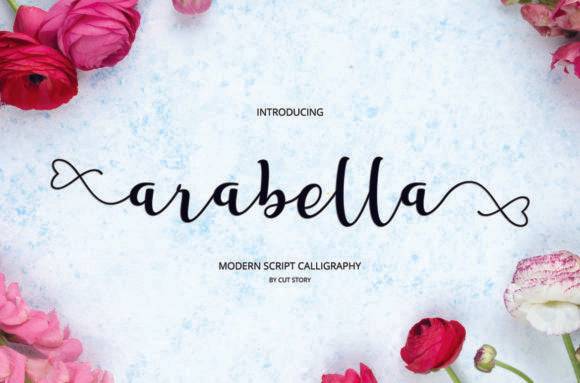
Fonte Arabella Script para identidade visual feminina e gráficos para redes sociais.
Arabella Script é inspirada na tipografia clássica e traz um estilo único para qualquer projeto de design. Esta fantástica fonte manuscrita é ideal para títulos de todos os tamanhos, bem como para blocos de texto com variações máximas e mínimas. Seja para web, impressão, imagens em movimento ou qualquer outra coisa, Arabella Script ficará espetacular.